Elegir una tipografía adecuada es esencial para transmitir un correcto mensaje a los lectores. Sin embargo, cuando un diseñador muestra distintas tipografías de una manera armoniosa, el sitio web en sí se muestra más sólido y estable e invita a los visitantes a explorar de manera más profunda.
Usar tipografías hechas a mano en el diseño gráfico o web no es una nueva tendencia, mucha gente ha usado sus propias tipografías hechas a mano para crear posters, cartas, anuncios y otros antes de que existiesen los ordenadores. Debido a que este tipo de fuentes gozan de gran creatividad y un elegante diseño, han ganado popularidad a lo largo de los años. Se pueden usar en cualquier tipo de proyectos, ya sean diseños de logos, posters, tarjetas de bienvenida, plantillas web, invitaciones de boda y mucho más, añadiendo un toque de personalidad y «hecho a mano». Con ellas puedes romper las reglas de un diseño o usarlas para añadir carácter a tu proyecto.
Por ello aquí os muestro 20 tipografías gratis hechas a mano para que puedas usarlas en tus proyectos de diseño web o gráfico. Todas son gratis y disponibles para uso personal y la mayoría para uso comercial, ¡así que a disfrutarlas!.
Mightype
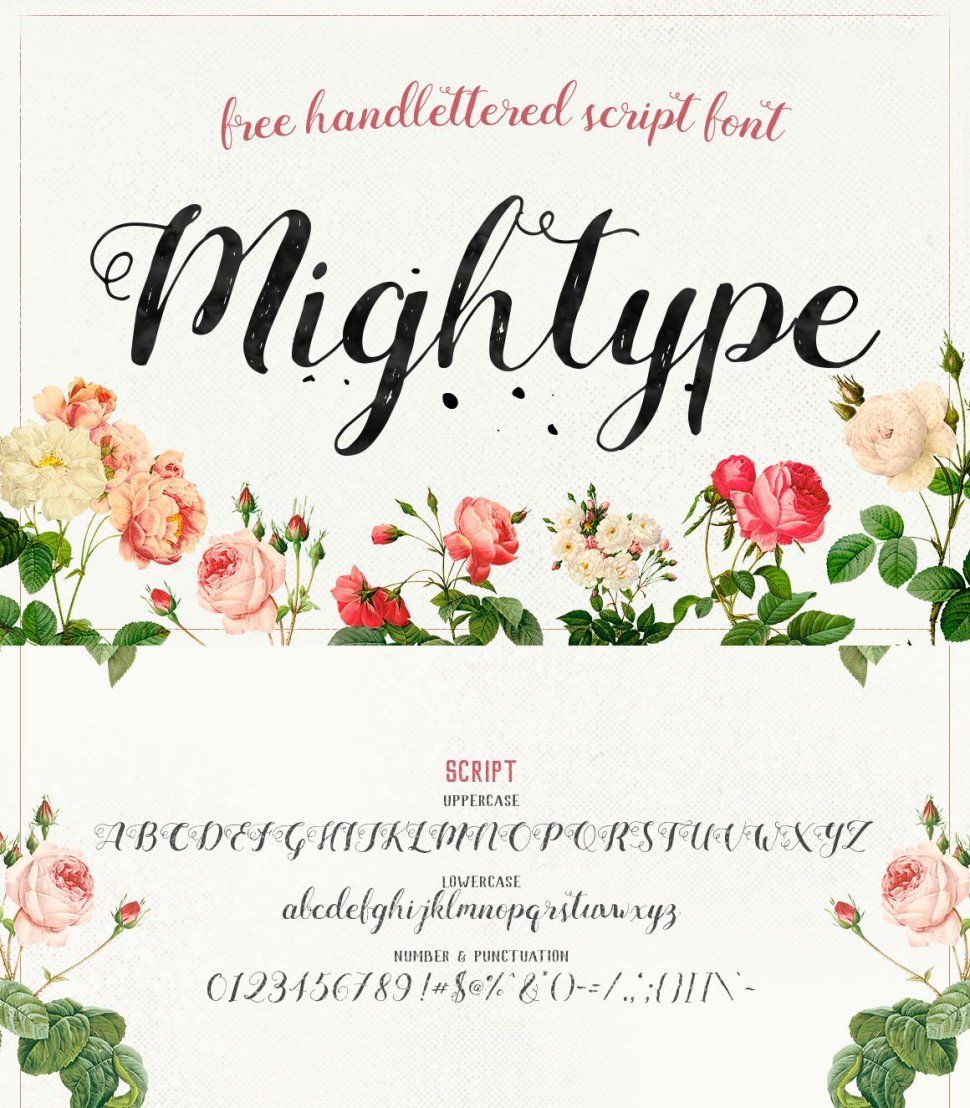
Bispo Nova
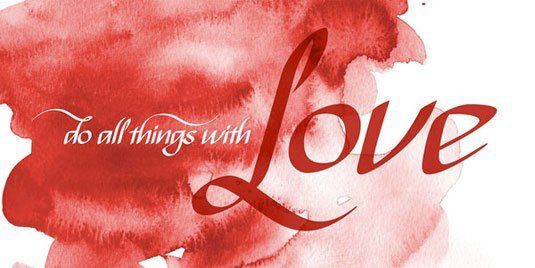
Landliebe
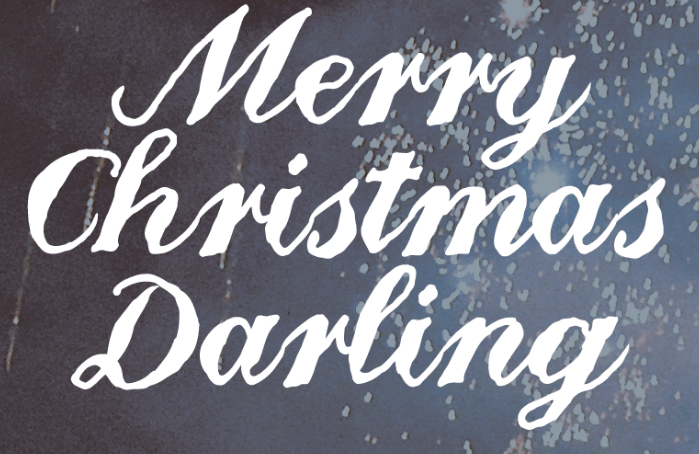
Rumi
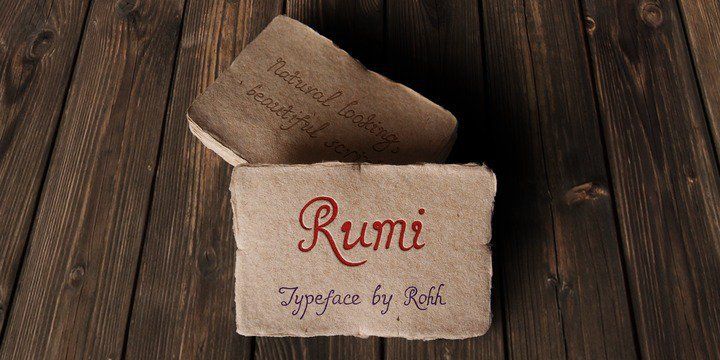
Playlist
Hello Stockholm
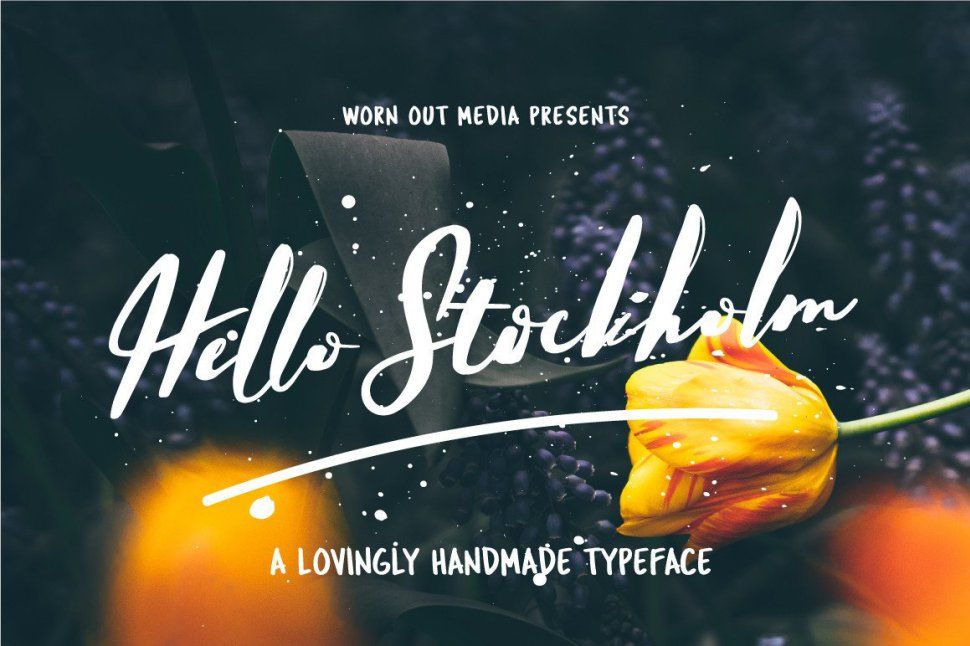
Wildera
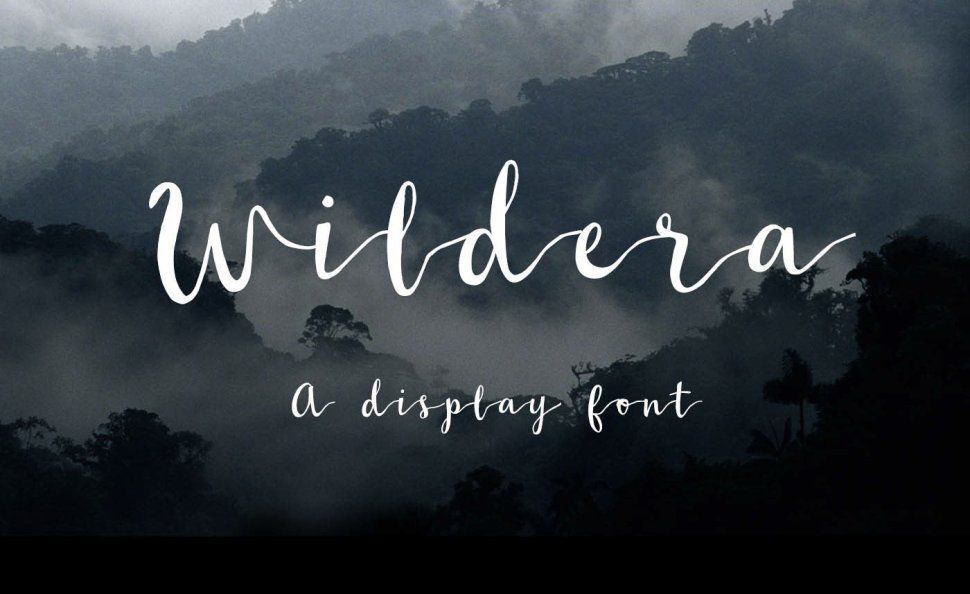
Arkana
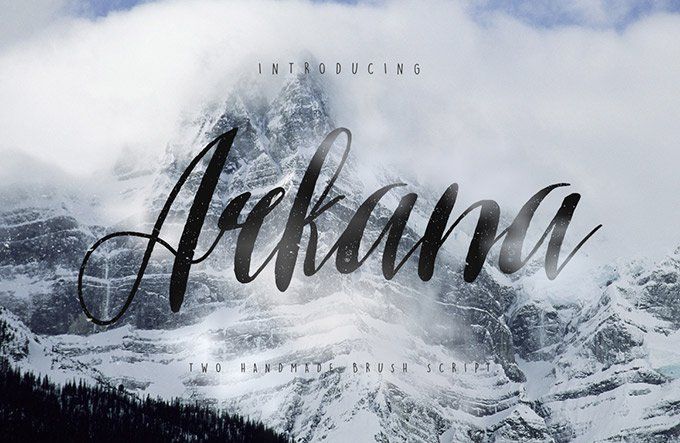
Yunus
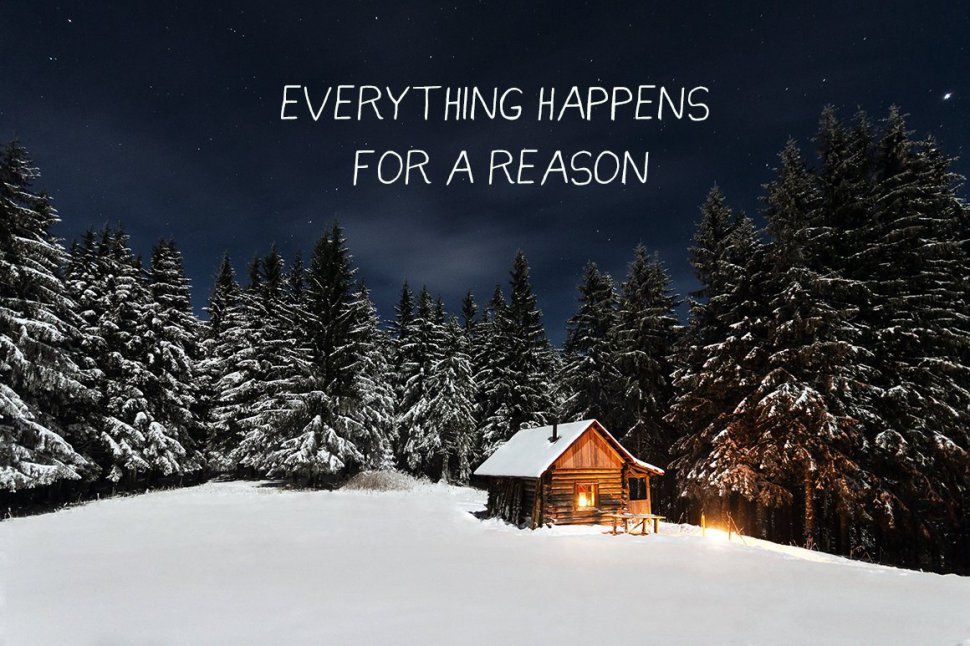
Reis
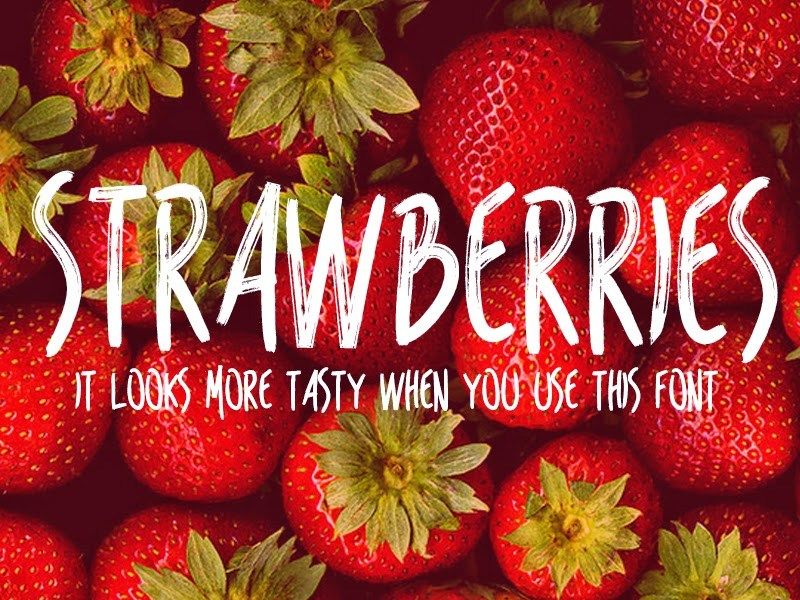
Ludicrous
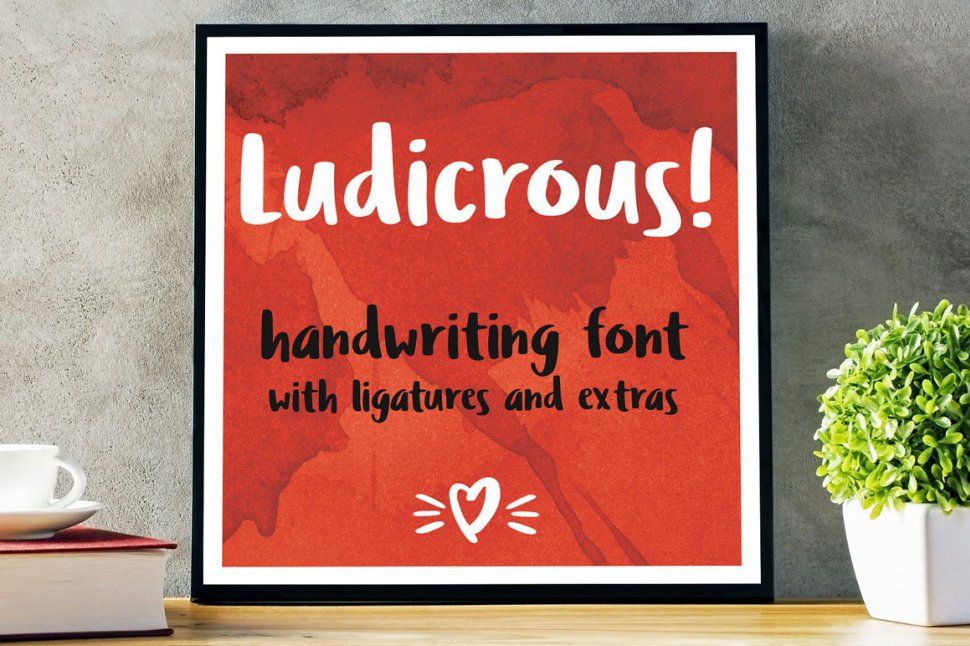
The Goldsmith
LSTK Bembo
Pops
Daniel
Magic Snow
Safirestone
Amirah
Kudeta
Noelan